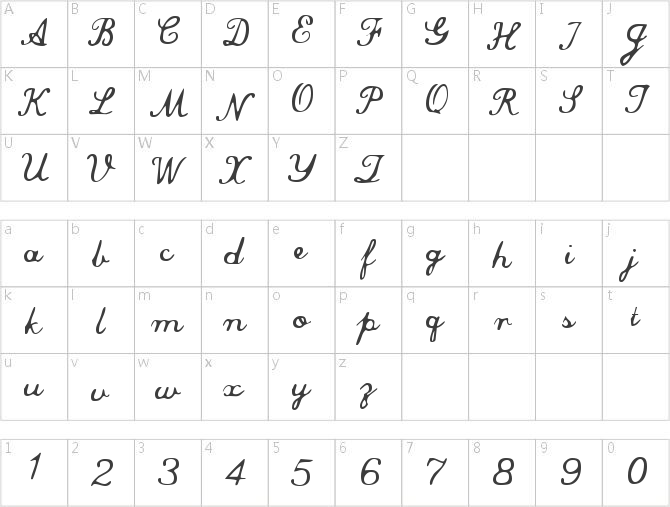
commersial_script 詳情頁
commersial_script
commersial_script字體字庫是一款讓人賞心悅目、百看不厭的英文字體,適合各類廣告和產(chǎn)品包裝設(shè)計應(yīng)用,字體大小0.04MB,格式為ttf字體,上傳用戶是rose,作者/版權(quán)方為未知